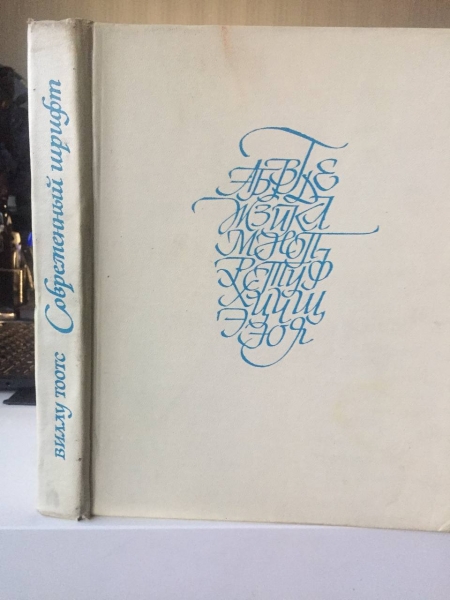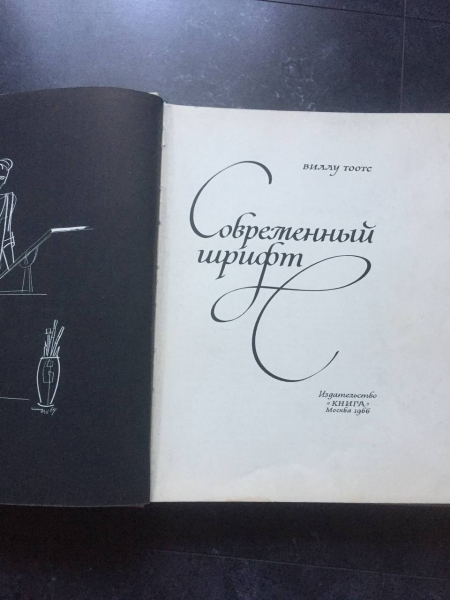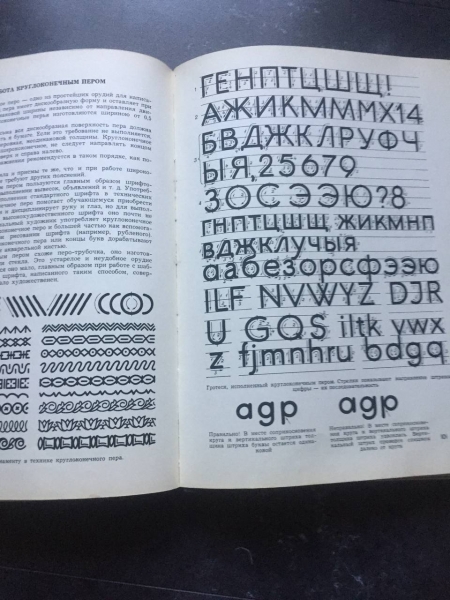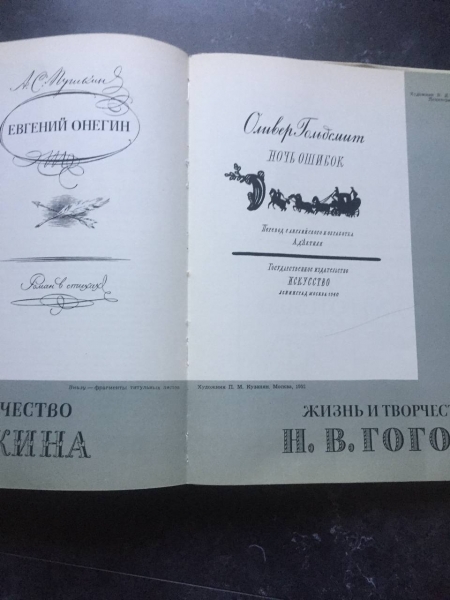
Тоотс Виллу. Современный шрифт.
Мы не представляем современную культуру без шрифта, и чем обширнее и разнообразнее становятся способы употребления шрифта, тем больше внимания мы должны уделять его качеству. В книге уделяется внимание как писанию шрифта, так и его рисованию. Большое значение придается типографским шрифтам. История шрифтов, техника рисования или письма и методика овладения тем или иным, разнообразие шрифтов и их назначение - все эти аспекты подробно рассмотрены в издании. Настоящая книга является не только учебником, но и сборником образцов, своего рода альбомом искусства шрифта. Автор имеет возможность познакомить с работами многих известных художников как советских, так и зарубежных. В книге представлены как алфавиты шрифтов, предназначенных для разнообразных целей, так и различные композиции. Значительная часть книги посвящена проблемам книжного искусства. Краткое содержание глав: История латинского шрифта. История русского шрифта. Работа ширококонечным пером. Работа круглоконечным пером. Работа кистью. Рукописная книга. Поздравительный адрес. Диплом и почетная грамота. Пригласительный билет и поздравительная карточка. Рисование шрифта. Орудия рисования шрифта. Построение букв. Межбуквенные пробелы. Межстрочные расстояния. Пропорциональность прописных и строчных букв. Принципы оформления шрифта. Выполнение шрифта для печати. Элементы книги. Суперобложка. Обложка и переплет. Титульный лист. Инициал. Фирменная марка. Плакат. Экслибрис. С указателем имен художников. С многочисленными цветными и черно-белыми иллюстрациями.